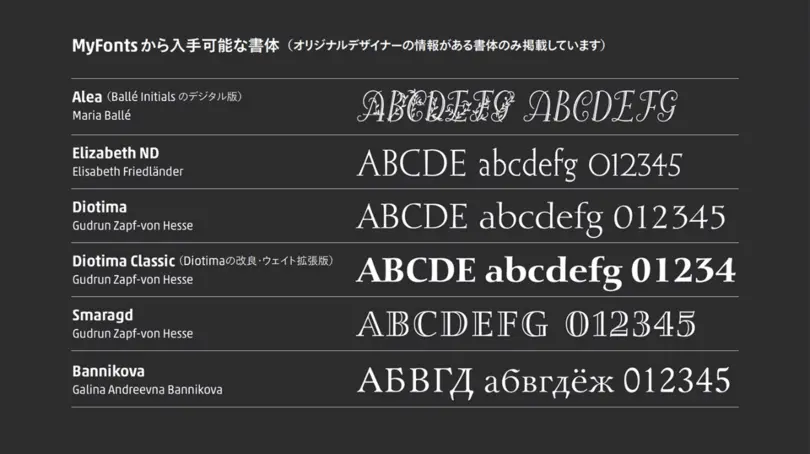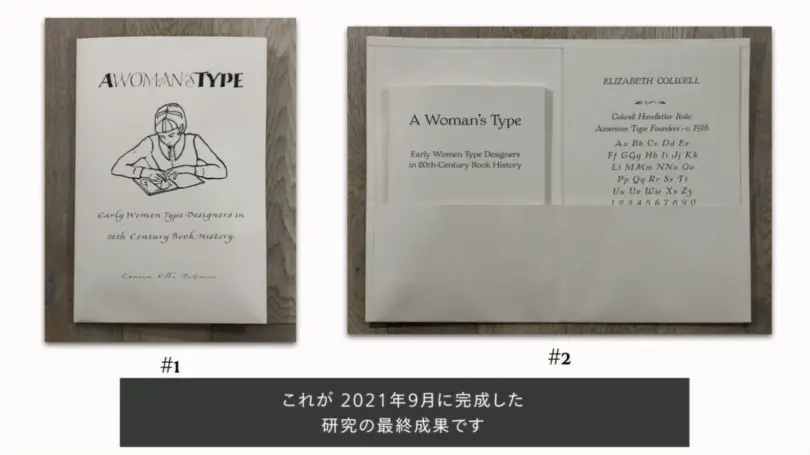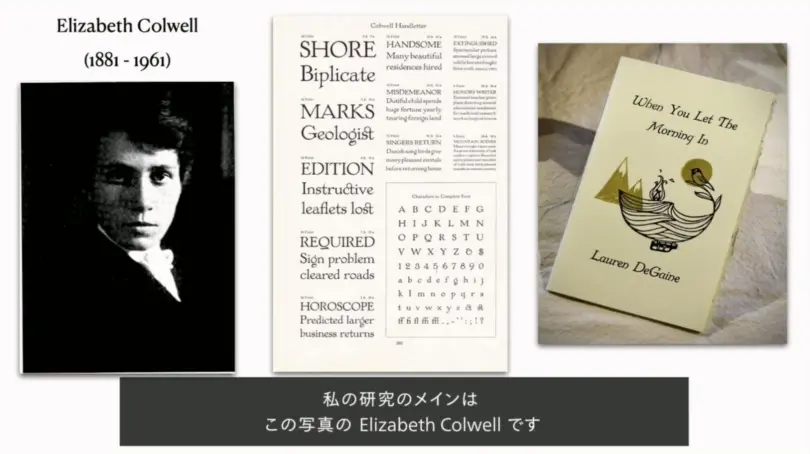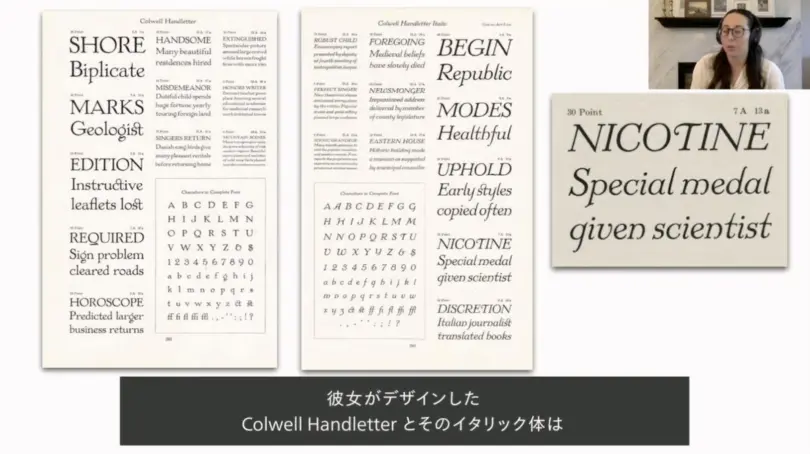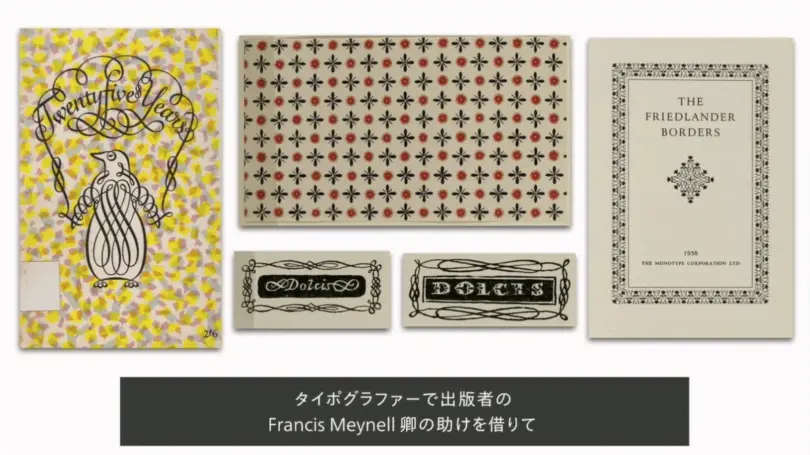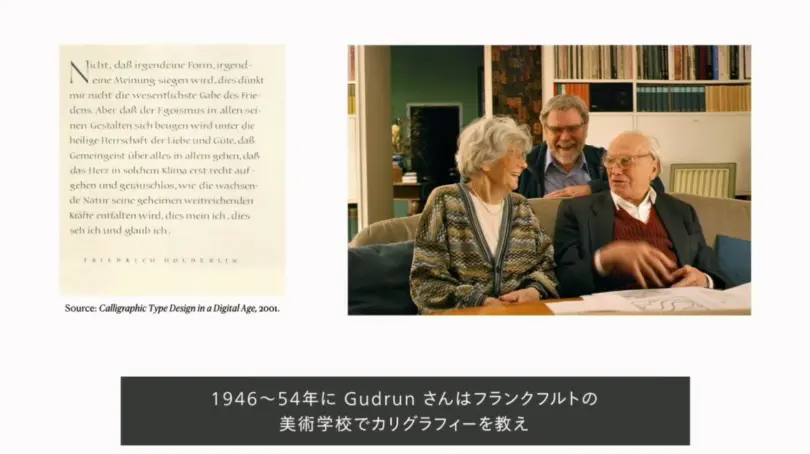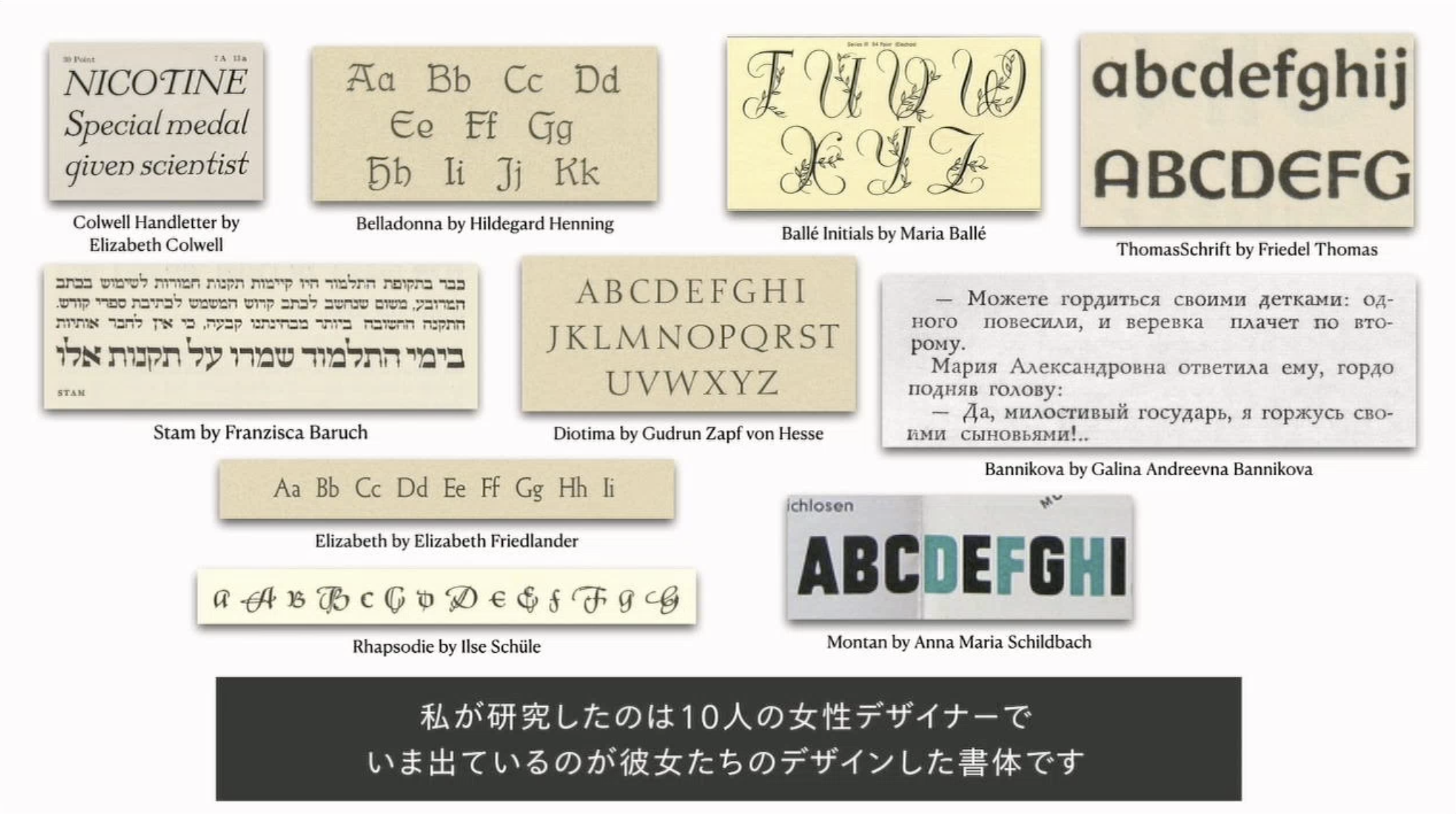
金属活字時代の女性タイプデザイナー
Type& 2022 Day 2 Session 2 - 金属活字時代の女性タイプデザイナーは、どのように生き、そしてどのような書体を生み出したのか。彼女たちのデザインについて活字見本とともに紹介。
Type& 2022 Day 2、Session 2は、 Lauren Elle DeGaine (ローレンエリー・ディゲイン)氏によるプレゼンテーションです。DeGaine 氏は大学時代に活版印刷に興味を持ち、金属活字時代に活躍した女性タイプデザイナーについて研究を開始。「A Woman’s Type: Early Women Type Designers in 20th-Century Book History 」という論文にまとめました。このセッションでは、この冊子から3人の女性タイプデザイナーの仕事を紹介。金属活字時代の女性タイプデザイナーは、どのように生き、そしてどのような書体を生み出したのか、活字見本とともに解説します。
写真左側が論文の表紙、ケースを開けて左に小冊子、右には活版印刷した5つの書体見本を収録。デジタル版はネットで無料閲覧可能。
研究の背景
DeGaine 氏が書いた論文「A Woman’s Type: Early Women Type Designers in 20th-Century Book History 」)。この論文では、パソコンの普及前に一般に販売されていた金属活字書体をデザインした女性が紹介されています。書体会社の制作部門の社員などは含まず、書体デザイナーとして名前の記録が残っている女性を対象としています。そのほとんどは生涯で1、2書体しかデザインしませんでしたが、レタリングやカリグラフィを学び、多くの書体デザインを任された人もいたそうです。20世紀初頭は、女性の社会進出とタイポグラフィ分野の両方にとって、特別な時代でした。
Elizabeth Colwell
セッションでは、 DeGaine 氏が論文冊子に掲載した10人のうち、3人の女性について説明しました。
写真中央の活字書体 Colwell Handletter とイタリック体は、 Elizabeth Colwell (エリザベス・コルウェル)がデザインし、American Type Founders が1916年に発表。
Colwell は、1881年、アメリカ、ミシガン州の小さな村の農家生まれ。彼女がレタリングした書体は1900年代初頭から見られます。レタリングとデザインの技術を広告にも生かし、アンティーク商の広告も手がけました。
当時、アーツ&クラフツ運動(イギリスのビクトリア朝時代後半、工業化への反動で生まれた運動)がアメリカで全盛期を迎え、手工業や工芸、美しく仕上げられた装飾的なデザインや作品がこの運動を通して再び注目を浴びていました。刺繍や陶芸など女性に求められていた仕事に注目が集まり、この流れを味方につけて、 世に出たのではないかと DeGaine 氏。
Colwell がデザインした書体 Colwell Handletter。今年の Type& の「&」の文字で使用。手書き感を残し、カリグラフィの影響を強く受けている。
Elizabeth Friedlander
次に、カリグラファー、タイポグラファー、グラフィックデザイナーの Elizabeth Friedlander (エリザベス・フリードランダー)が紹介されました。
Friedlander は、1903年に文化的で裕福なユダヤ系ドイツ人の家庭に生まれ、ベルリン・アカデミーでタイポグラフィとカリグラフィを習得。才能あるアーティストであり、音楽家でもありました。人気女性雑誌『Die Dame』のレイアウトや見出しのデザインを手がけ、1935年までドイツで様々な出版社の書籍デザインをしています。
1935年にはヒトラーとナチスがドイツで実権を握り、グラフィックデザイン協会の通達により、ユダヤ系の Friedlander は母国ドイツで働くことができなくなりました。1936年にはイタリアのミラノへ移り、有名出版社のデザイナーとして勤務。その後、1938年にイタリアの人種法により、アメリカへ移住せざるをえなくなります。当時ドイツからアメリカへの亡命者が多く、受け入れに時間がかかったため、1939年にイギリスに移住し、デザイナーとして再び働き始めました。
Friedlander は、第二次世界大戦後もイギリスに残り、有名なタイポグラファー、 Jan Tschichold (ヤン・チヒョルト)からの誘いを受け、1940年代後半から Penguin Books 向けの作品を手がけました(写真左)。また、1940年代後半から1950年までは製本用の装飾紙を制作(中央)。1952年には Linotype 向けの、1958年には Monotype 向けの飾り罫も制作しました(右)。1960年代前半、アイルランドのキンセールへ移住して工芸家となり、1984年にその地で亡くなりました。
Friedlander がデザインした書体 Elisabeth(金属活字の書体名で後のElizabeth)。1938年にドイツの Bauer 鋳造所が発表。汎用性が高く、読みやすい。イタリックはクラシックながらも優美さがあり、フォーマルな便箋や招待状、タイトル文字などの用途によく合う。
Gudrun Zapf von Hesse
Gudrun Zapf von Hesse (グドルン・ツァップ=フォン・ヘッセ)は、カリグラファーであり、アーティスト、装丁家でもあります(詳細は写真左の書籍『Gudrun Zapf von Hesse: Bindings, Handwritten Books, Type Faces, Examples of Lettering and Drawings』参照)。
1918年にドイツで生まれ、20世紀から21世紀にかけて書体デザインでキャリアを築きました。1934年から1937年にかけて、ワイマールの製本工房の見習いになったのをきっかけに、カリグラフィを学び始める。1940年に製本の修士号を取得し、翌年にはレタリングのプログラムを修了。
1946年にフランクフルトに移住し、Bauer 鋳造所で働いていた頃、鋳造所の敷地内に自身の製本工房を開設。活字の製造技術を学び、Hesse Antiqua の真鍮活字を完成させました(2018年にデジタル化)。
1946年から54年にかけてフランクフルトの美術学校でカリグラフィを教え、1948年の展覧会ではフリードリヒ・ヘルダーリン著の書簡体小説『Hyperion to Diotima』を書いたカリグラフィ作品(写真左側)を展示。当時、Stempel 鋳造所でアートディレクターをしていた Hermann Zapf (のちに彼女の夫となる、20世紀のタイポグラフィ界の巨匠)がその展覧会でこの作品を見て、彼女をStempel 社に招聘し、製本工房を開設。これがタイプデザイナーとしてのキャリアの第一歩になりました(写真手前が Zapf 夫妻、奥は当時の Linotype 社のマーケティング部長。小林章が撮影)。
1991年、Gudrun は Rochester Institute of Technology から Frederick W Goudy 賞を受賞。1972年から2019年12月13日に101歳で亡くなるまで、ドイツのダルムシュタットで暮らしました。
代表作となる書体 Diotima は、1951年にステンペル社から発売。Linotype 社が Diotima のローマン体とイタリック体を発表したほか、2008年に Gudrun と小林が一緒にデザインし、8ウェイトに増やした Diotima の改刻版である Diotima Classic(写真#2)が発売されました。Ariadne Initials(写真#3)は1954年に Stempel 社が発表。カリグラフィの要素を持つスワッシュレターの大文字もあります。1954年に Stempel 社が発表した Smaragd(写真#4)は銅版印刷の文字からインスパイアされた書体です。
20世紀後半に技術が進化する中、 Gudrun は写植書体やデジタル書体を作り続けました。1980年代から90年代にかけてはデジタル書体をデザインしましたが、彼女は「パソコンに支配されたくない」と語っており、手を使って書体をデザインする昔ながらの手法を好んだそうです。パソコンを使えば時間の節約になることはわかっていましたが、「書体作りに大事な人間らしさが失われる」とも考えていたとのこと。書体制作の中心にはカリグラフィがあり、その研究の積み重ねが新しい書体を生み出す基盤になるとグ Gudrun は語っています。
セッションの中で Degaine 氏は3名の女性デザイナーの生涯と書体を紹介。論文はオープンアクセスで以下のウェブサイトから閲覧可能です。
A Woman’s Type: Early Women Type Designers in 20th-Century Book History
Hesse Antiqua を使った活版印刷。 Gudrun とタイポグラファーの Ferdinand Ulrich(フェルディナンド・ウルリヒ)が共同で制作したデジタルフォントを使って、カリフォルニアの活版職人 Matt Kelsey が樹脂凸版で印刷。
Q & A 質疑応答
Elizabeth Colwell が特に他のデザイナーと違う点はありますか?
DeGaine 氏:他の女性は芸術一家、あるいは裕福な家庭出身だったり、家族の中に出版に携わる男性がいたりしますが、 Colwell は違いました。彼女の家族は農家で、 Colwell 人生のほとんどは未亡人となった母と借家住まいで暮らし、労働者階級の出身で経済的に自立していました。これが女性デザイナーと Colwell また、書籍関連の媒体が中心だった他のデザイナーに比べ、 Colwell の作品は美術寄りだったと言えるでしょう。他のデザイナーは装丁やレタリング、製本やカリグラフィが中心でしたが、 Colwell は絵画やエッチング、木版刷りなど美術作品で実績を積みました。
女性、男性それぞれの書体デザイナーが同様のコンセプトで書体をデザインした場合、どのような部分に違いや特徴が出ますか?
DeGaine 氏:書体のデザイン要素にジェンダー的な要素はないと思います。実際は女性がデザインした書体を女性がデザインしたと後から知って、女性的な特徴だと思い込んでしまうのではないでしょうか。(書体が)繊細、かわいらしい、あるいは女性的と決めつけてしまうのです。女性も男性もどんな書体でもデザインできますが、デザイナーについて世間が知ったとき、そういった枠に当てはめがちです。デザインに性別の違いが現れるかどうかは議論の余地があるかもしれません。
女性デザイナーによる金属活字書体のうち、デジタル化され MyFonts から入手可能な書体のリスト(オリジナルデザイナーの情報がある書体のみ)
小林章から一言
このセッションでは、20世紀初頭の女性金属活字デザイナーを紹介しましたが、同じ時代に書体デザイナーではない立場でタイポグラフィに関わった女性もいました。20世紀前半から中頃に活躍した Beatrice Warde(ベアトリス・ウォード)です。
Monotype では、ニューヨークの Type Directors Club と連携して、彼女の名前を冠した奨学金制度「Beatrice Warde Scholarship」を設けました。クリエイターを目指している女子学生を対象とした奨学金で、世界中のどこにいてもオンラインで申し込みができます。審査員も女性で、最も優秀とみなされた一人に奨学金5000ドルが贈られます。
DeGaine さんと知り合ったきっかけは、私が撮影した Zapf さんご夫妻の写真を修士論文の締めくくりに使わせてほしいというメールを受け取ったことでした。その写真のつながりで、Type& のセッションをお願いすることになりました。
Type& は Gudrun さんとも関わりが深く、2018年の Type& の会場でグドルンさんの展覧会を開きました。グドルンさんの書体 Diotima の金属活字を使って嘉瑞工房の髙岡昌生さんが活版印刷した用紙に、グドルンさんと交流のあった日本のカリグラファーが書いたカリグラフィ作品を展示するという、夢のようなイベントでした。 Gudrun さんは2019年に101歳でお亡くなりになったのですが、日本の私たちにも大きな遺産を残してくれました。